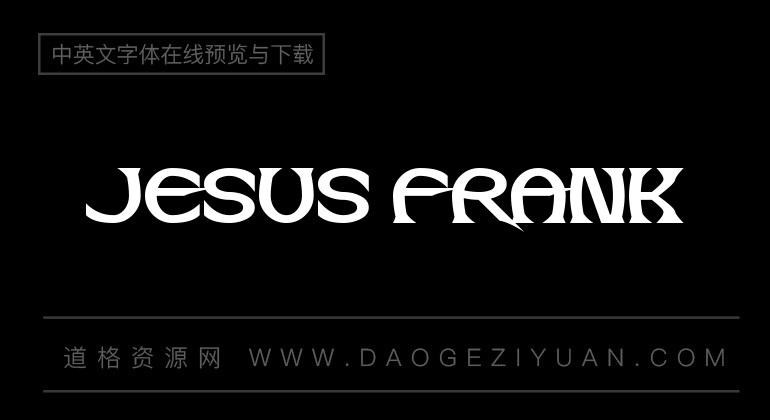
Jesus Frank
Jesus Frank字体是一款由西班牙设计师Jesus Frank所创作的一款复古字体,它具有强烈的西班牙风格,以及深厚的历史感。它的字体特点是拥有深厚的古典感,同时又具有现代的设计元素,可以满足不同的设计需求。此外,它还具有多种字体样式,例如英文、拉丁文、希腊文、俄文等,可以满足不同语言的需求。
Jesus Frank是一款非常不错的手写艺术字体,具有很好的视觉感,适合于文化类的宣传设计、商业类品牌的广告和产品包装设计以及个性化文字排版等较多场景。